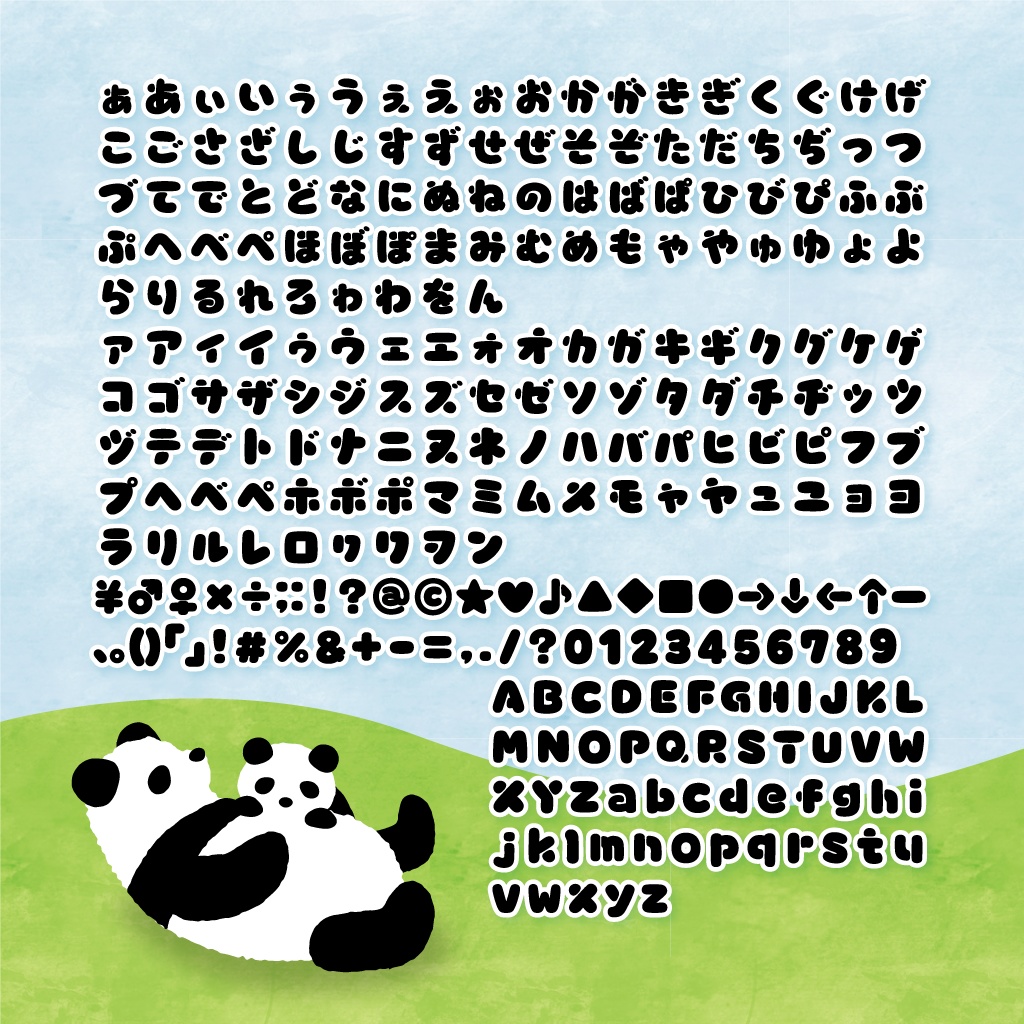
子パンダフォント
※無料版はカタカナ・数字・一部記号のみとなります。 無料版も商用可能です。 コロコロとしたかわいい子パンダをイメージして制作しました。ステンシル風のアクセントがポップな印象のフォントです。 【通常版】収録文字 ぁあぃいぅうぇえぉおかがきぎくぐけげこごさざしじすずせぜそぞただちぢっつづてでとどなにぬねのはばぱひびぴふぶぷへべぺほぼぽまみむめもゃやゅゆょよらりるれろゎわをんァアィイゥウェエォオカガキギクグケゲコゴサザシジスズセゼソゾタダチヂッツヅテデトドナニヌネノハバパヒビピフブプヘベペホボポマミムメモャヤュユョヨラリルレロヮワヲン ¥♂♀×÷;:!?@©★♥♪▲◆■●→↓←↑ー、。()「」!#%&+-=,./?0123456789 ABCDEFGHIJKLMNOPQRSTUVWXYZabcdefghijklmnopqrstuvwxyz フォントデータ形式:OpenType 印刷物・立体制作物・web・ゲーム・映像・電子書籍・LINEスタンプ(絵文字スタンプは不可)などにお使いいただけます。 変形・加工も可能です。 ロゴマーク等、商標登録する際は加工した画像のみ商標登録できます。 禁止事項 ・公序良俗に反する目的、誹謗・中傷目的での利用。 ・ロゴマーク等、商標登録すること。 ・フォントファイルのみの譲渡・再配布・販売。